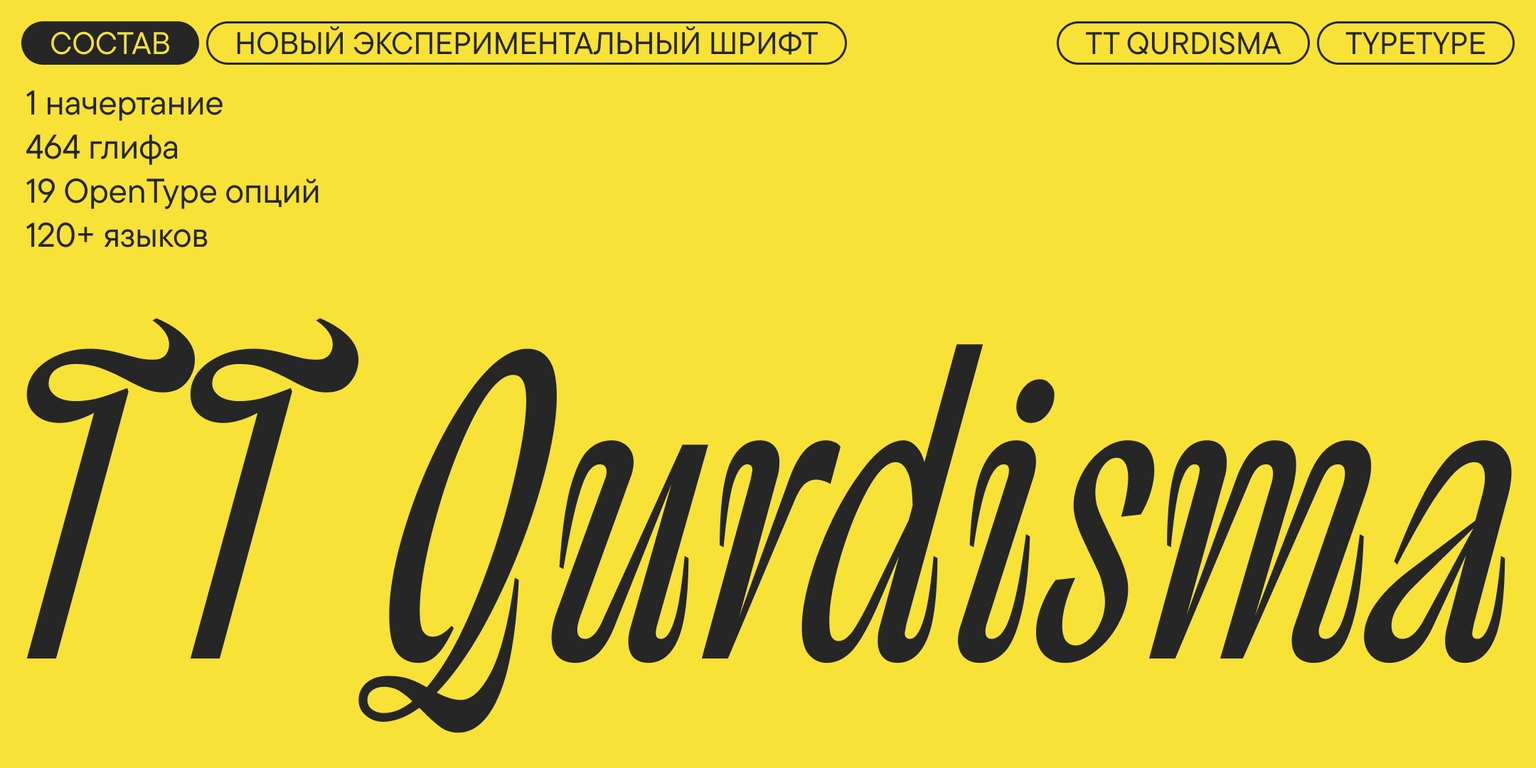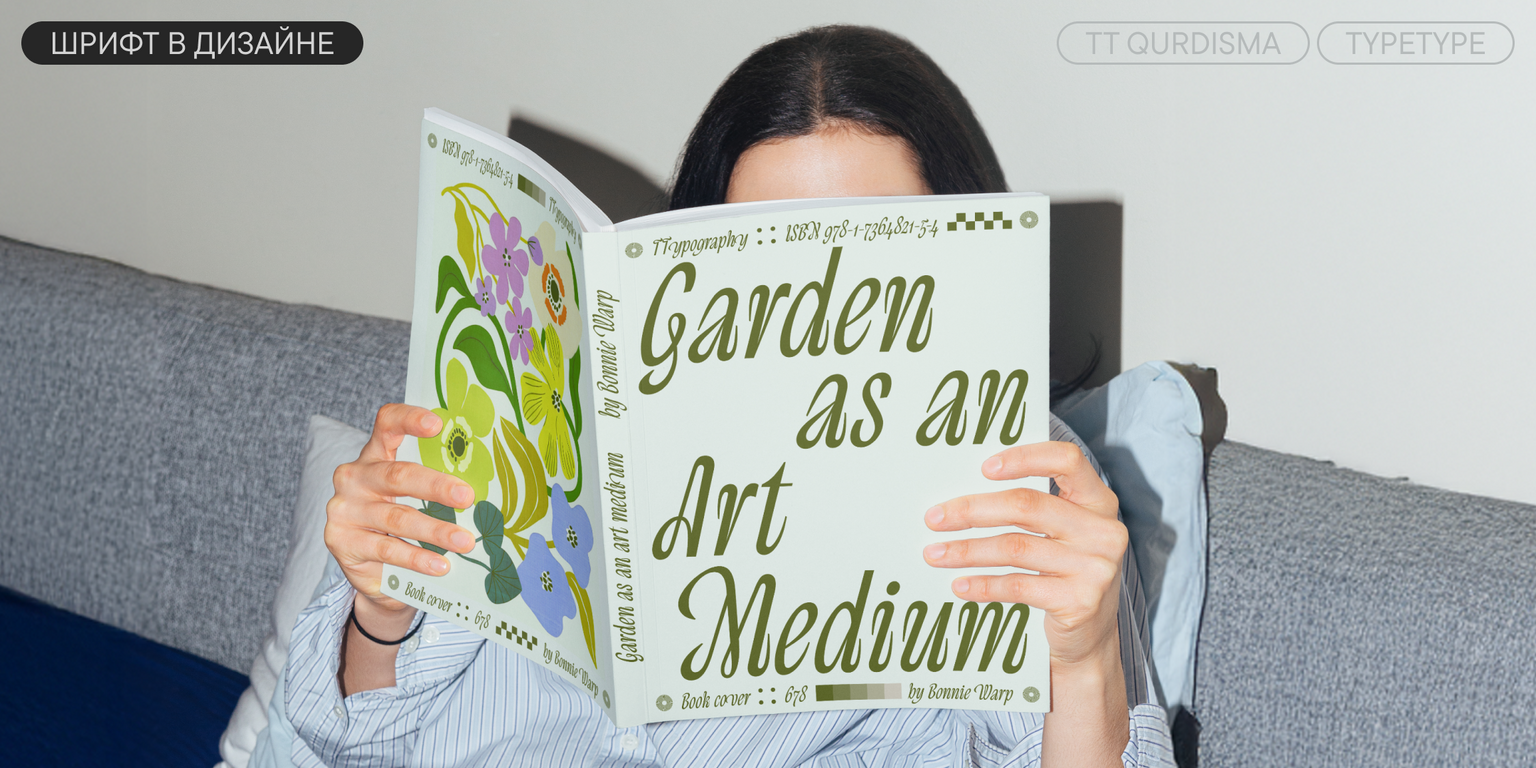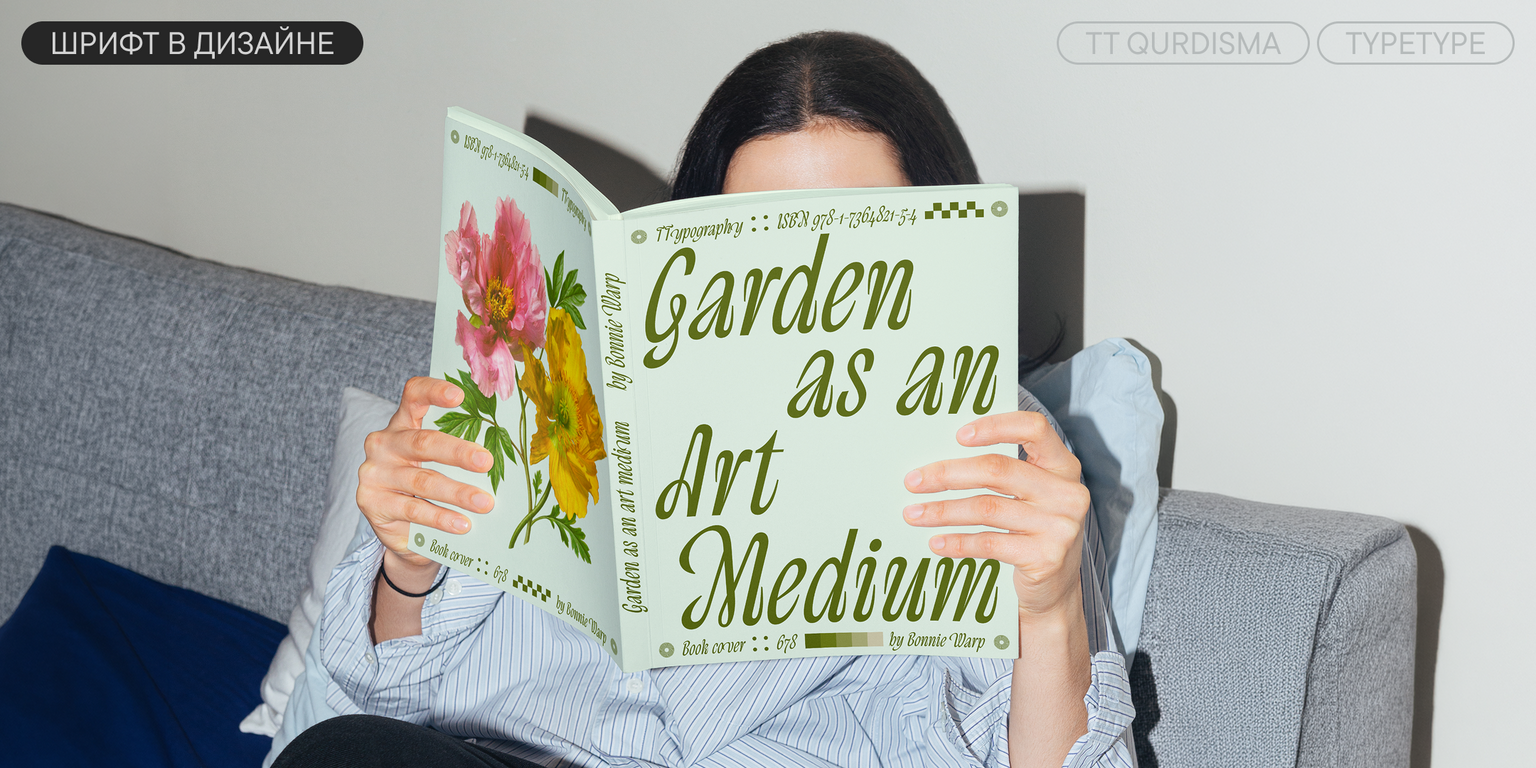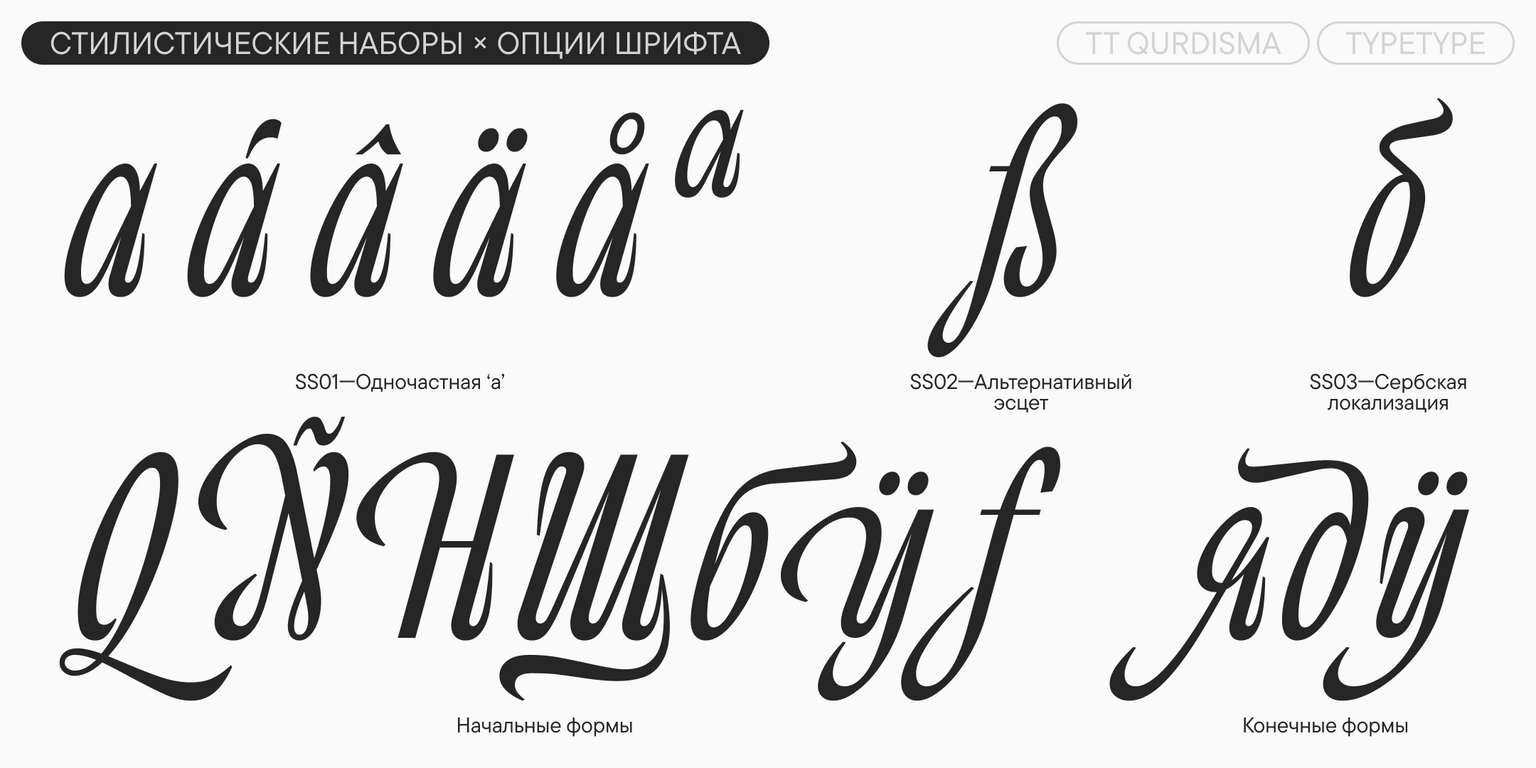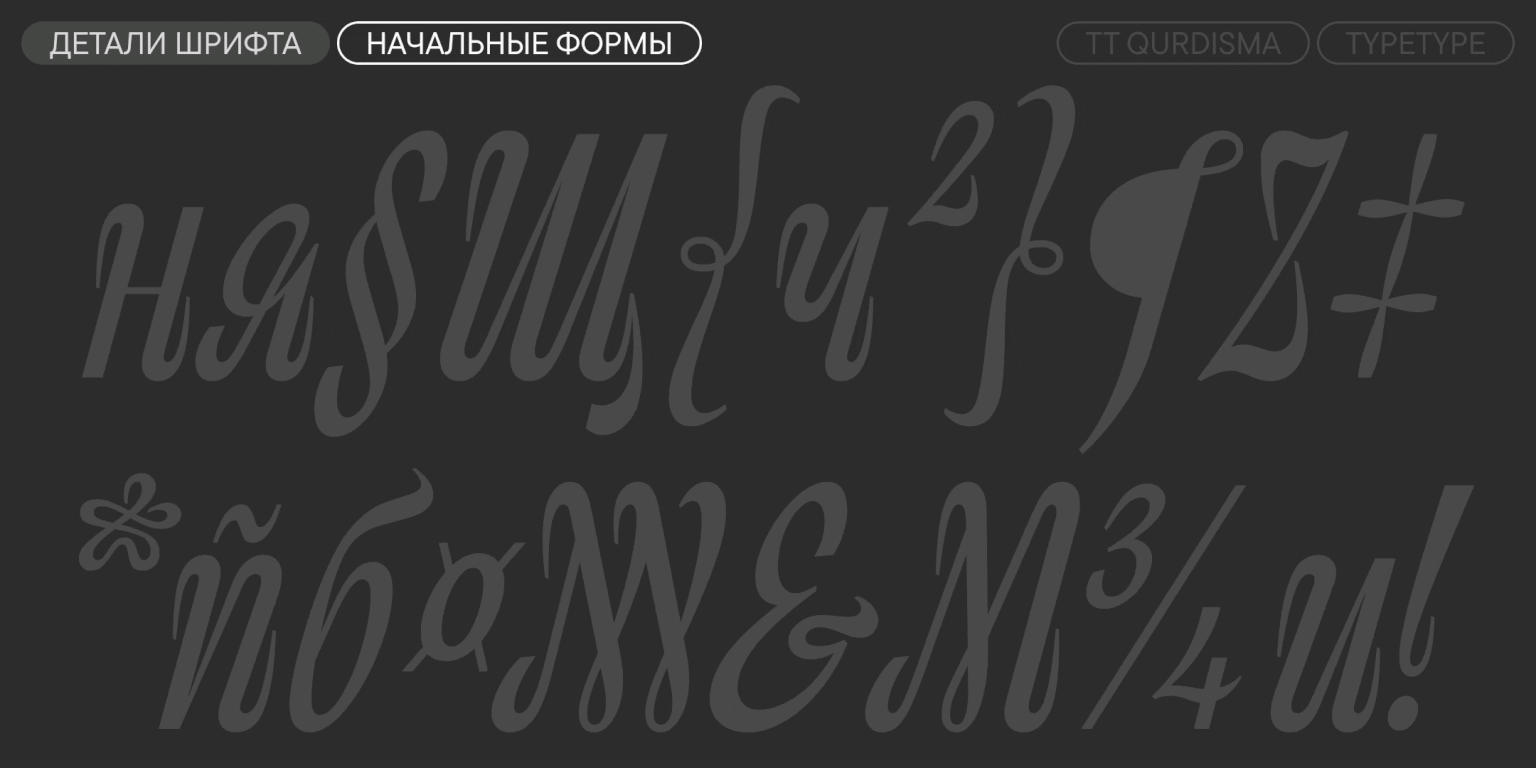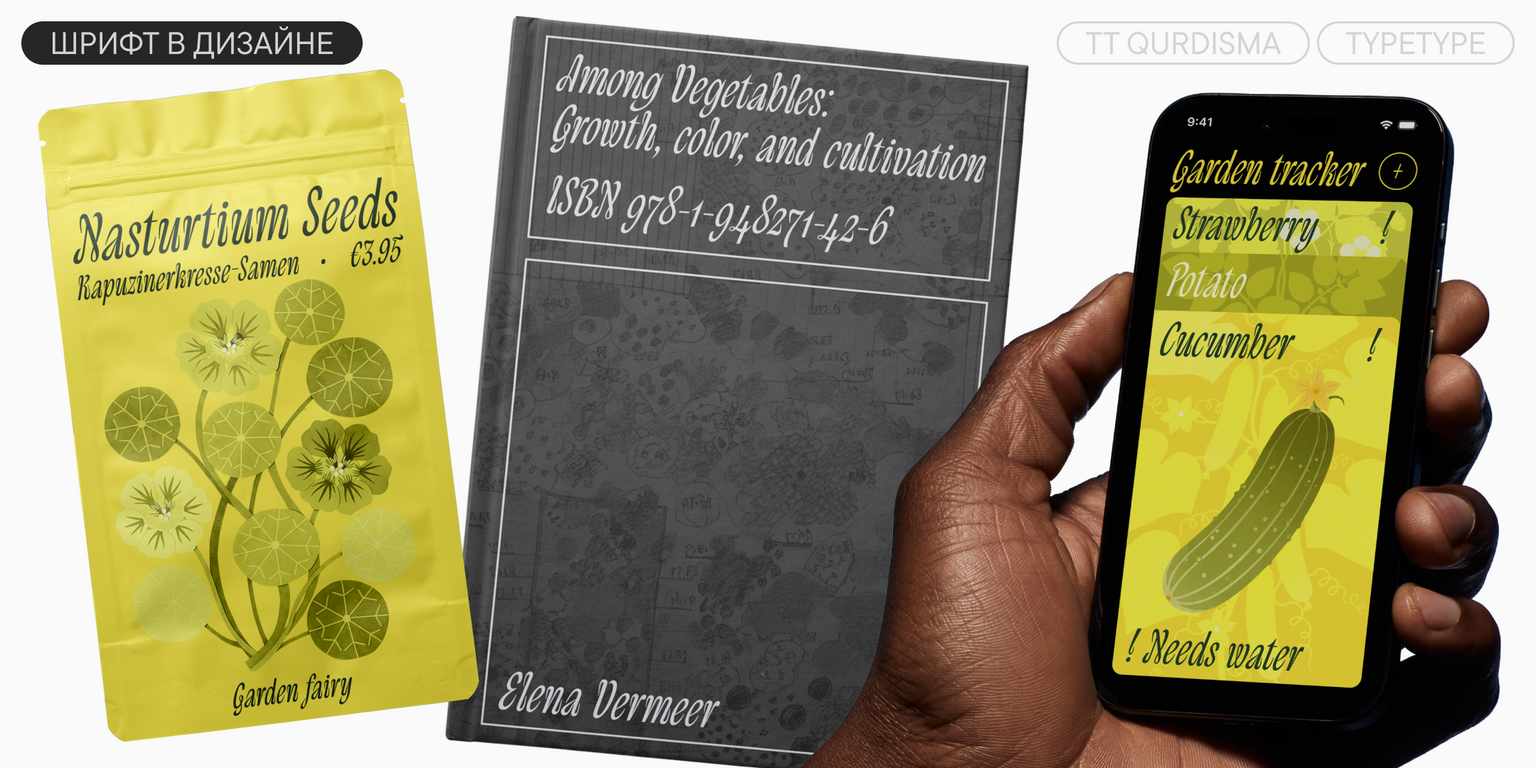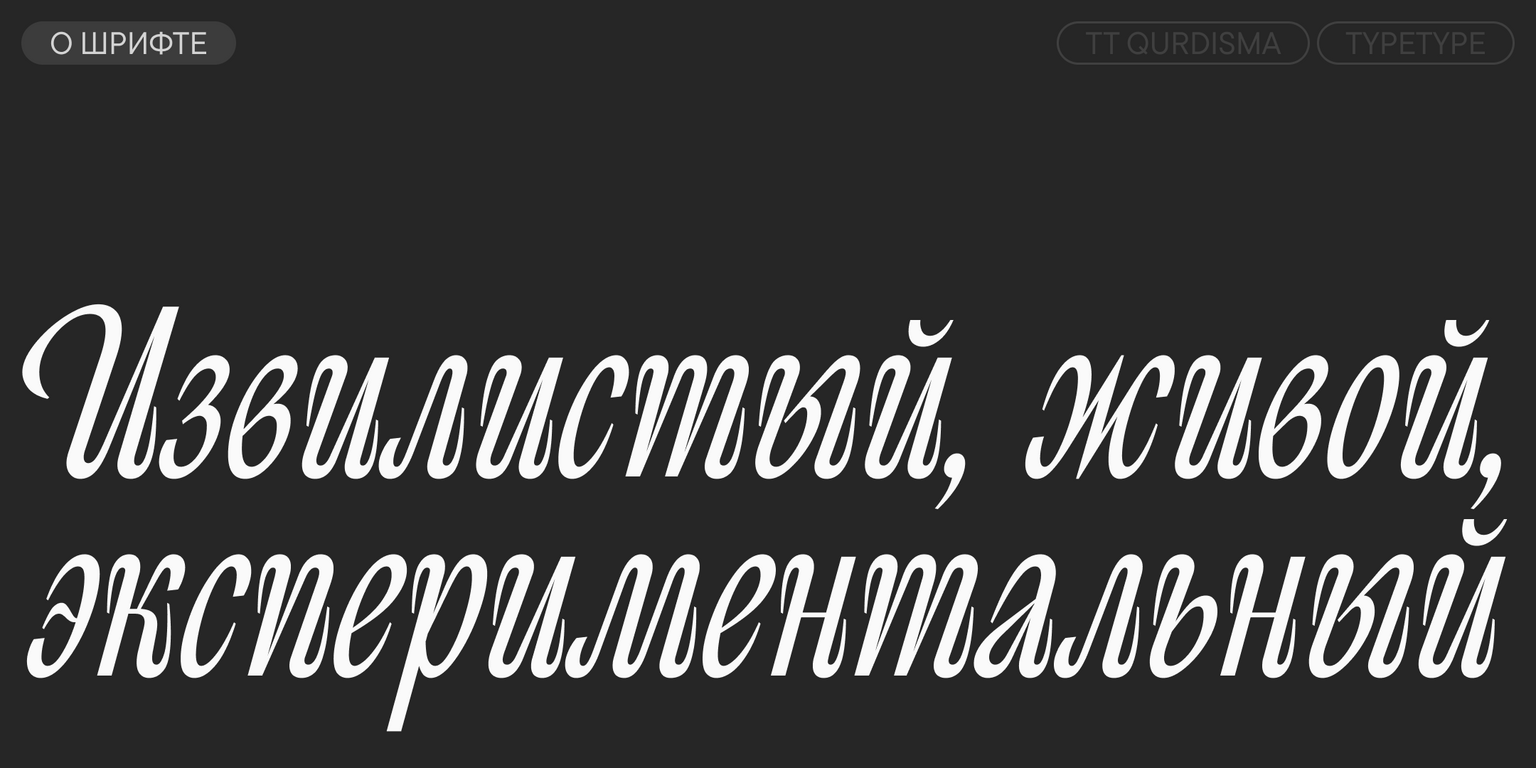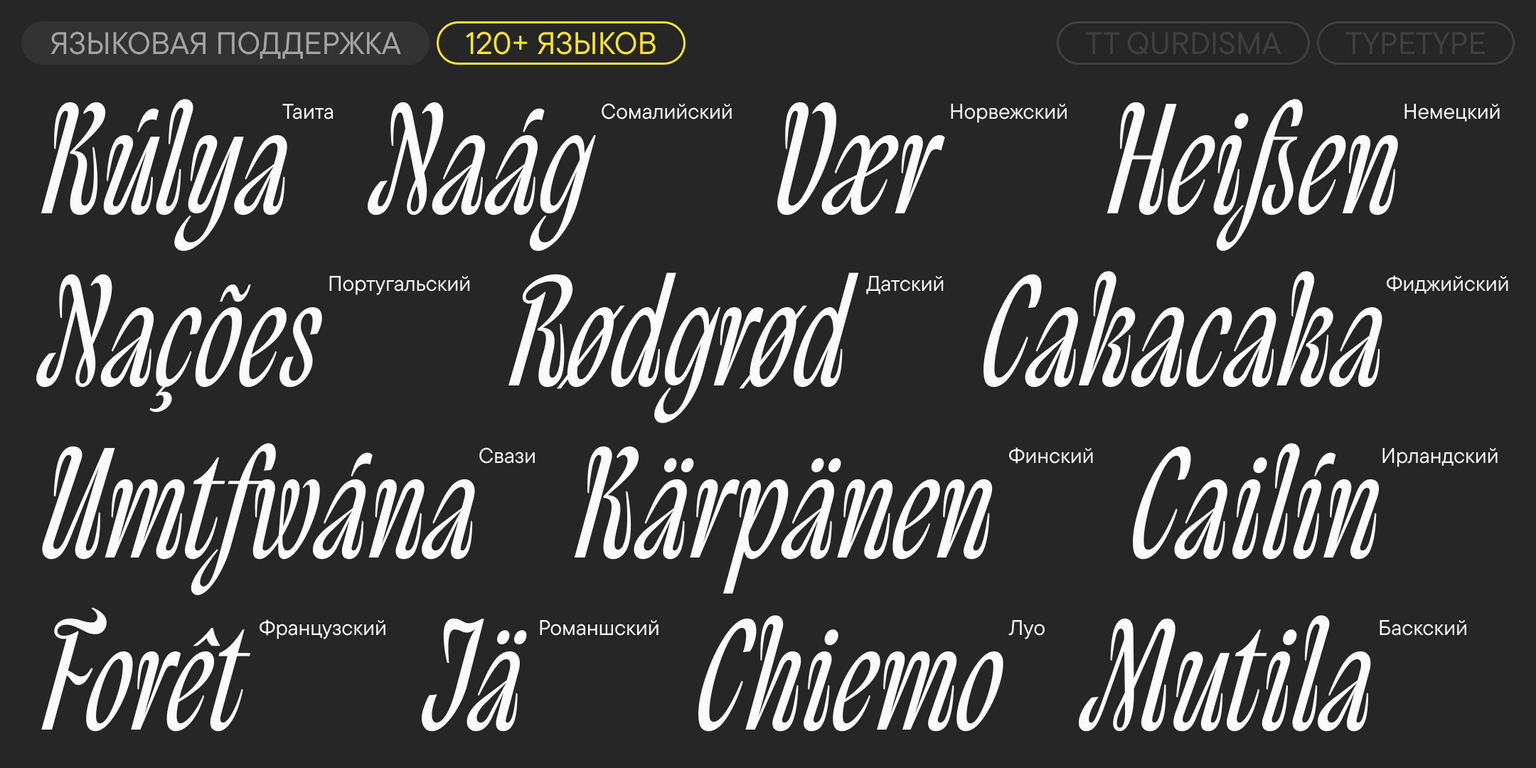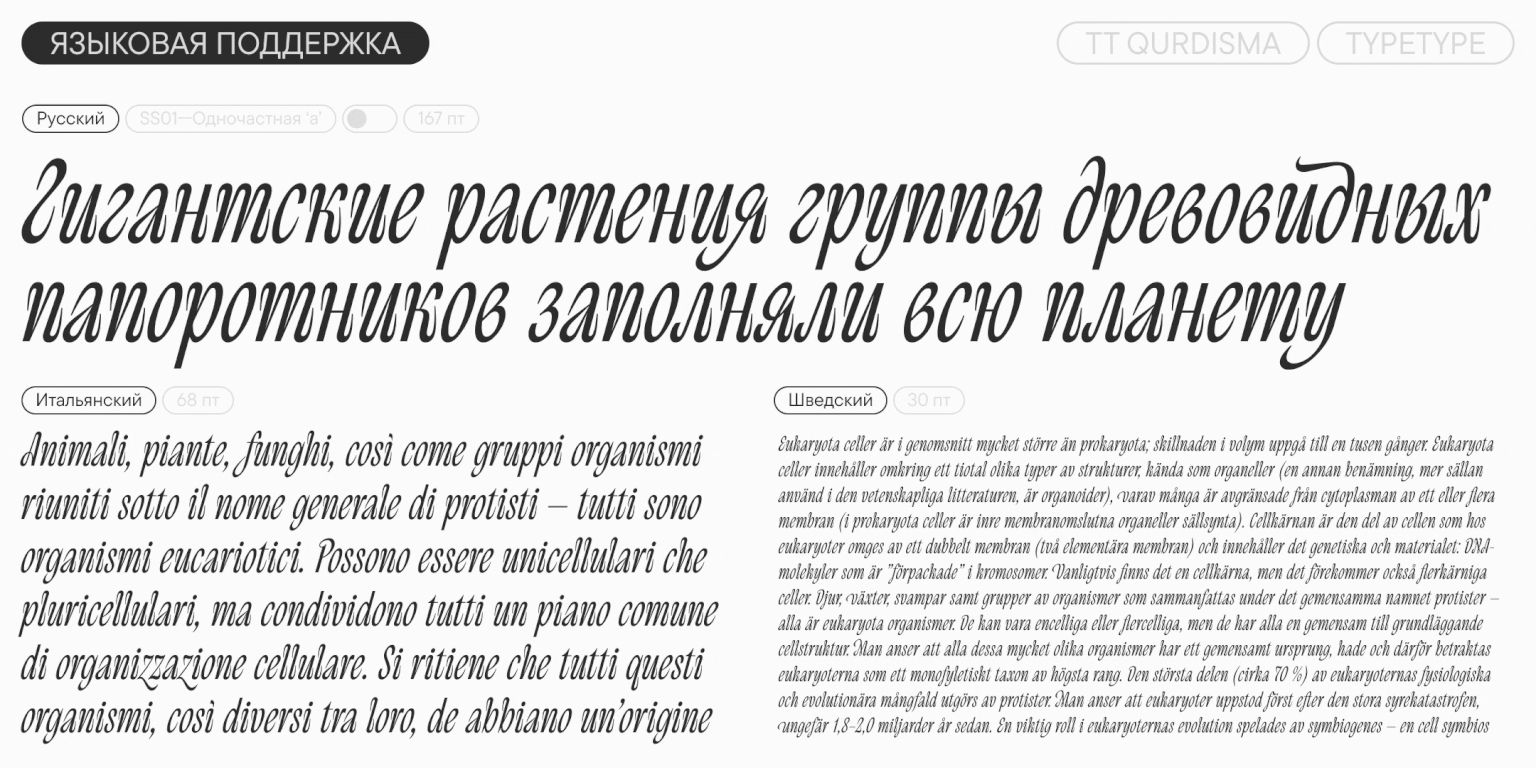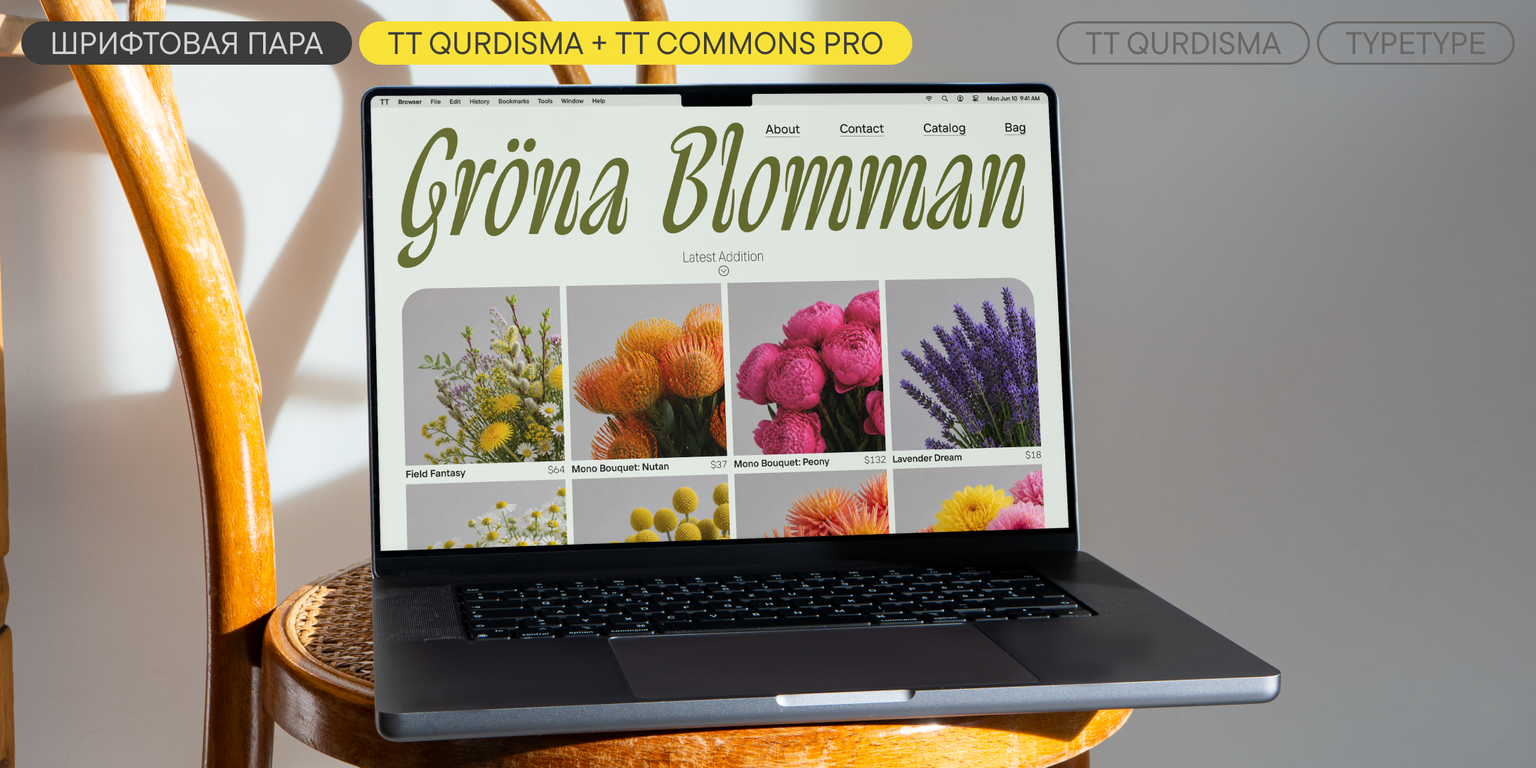
TT Qurdisma
TT Qurdisma — ТТ Курдизма
Произносится «ТТ Курдизма». Слово «Qurdisma» происходит от греческого κούρδισμα, в переводе — «извилистый». Буквы TT являются аббревиатурой названия компании.
TT Qurdisma — узкий и плотный декоративный шрифт, напоминающий причудливое растение. Вьющиеся, плавные контуры рождают растительный орнамент.
О гарнитуре TT Qurdisma
Встречайте новый TT Qurdisma — извилистый и живой шрифт, напоминающий причудливое растение!
TT Qurdisma — экспериментальный дисплейный шрифт, проросший в оранжерее нашей творческой лаборатории. В основу эксперимента легла идея смешать в единую концепцию два случайных параметра: «плотный спейсинг» и «настоящий италик». В результате получился шрифт с функциональной кассой и уникальным характером, полный красивых деталей.
Название гарнитуры происходит от греческого κούρδισμα (извилистый). Это узкий, плотный шрифт с закручивающимися внутрь знаками. Рисунок вдохновлён растениями (водоросли, папоротники, суккуленты). Вьющиеся, плавные контуры рождают растительный орнамент. Круглые знаки более наклонные, чем прямые, что придаёт ещё больше динамики. У прописных из-за закрученных форм и обилия петелек более сложный ритм, а строчные выглядят спокойнее, так как в них часто повторяется похожий элемент — арка со «щупальцем» на конце штриха.
Шрифт состоит из одного наклонного начертания, графика которого отсылает к формам настоящего италика. Буква «а» в основном наборе двухчастная, но есть стилистический набор с одночастной версией. Также мы добавили два варианта эсцет (ß), альтернативы с росчерками для некоторых букв и лигатуры.
TT Qurdisma — декоративный шрифт, который идеально подойдёт для сферы моды, культурных спецпроектов или брендинга.
В TT Qurdisma входит:
• 1 наклонное начертание;
• 464 знака;
• 19 OpenType функций;
• 120+ языков.
ss01 | Single-storey a
init | Initial Forms
fina | Medial Form #3
liga | Standard Ligatures
dlig | Discretionary Ligatures
ss02 | Alt. Eszett